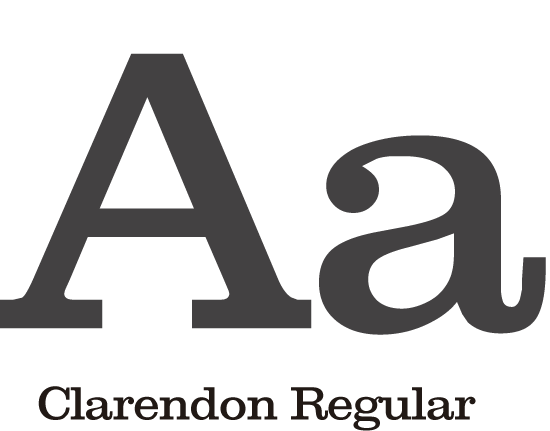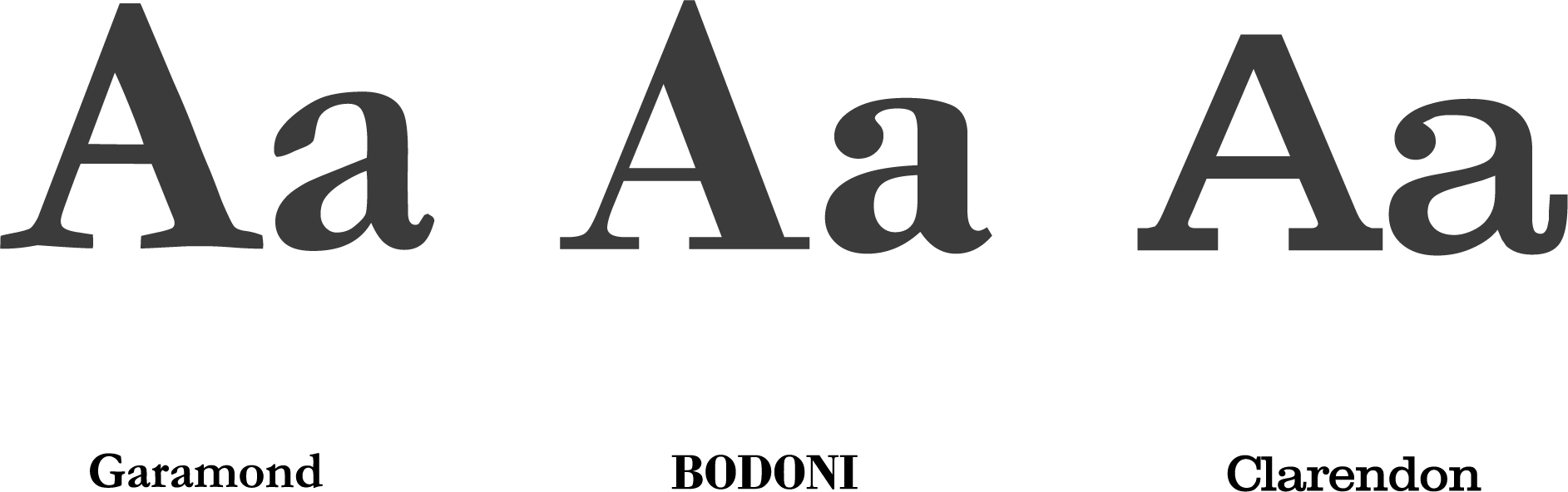
2.- Tipografía Colaborativa – Clasificación Tipográfica, Serif
Segundo Test sobre el correcto uso de la Tipografía en el diseño sobre la segunda animación de los vídeos Tipografía Colaborativa - Clasificación Tipográfica, Serif
1.- ¿Cuáles de las siguientes tipografías presentan Serif?
2.- De acuerdo con la Clasificación Tipográfica ¿Cuáles de las siguientes tipografías pertenecen al estilo Romano Antiguo?
3.- El estilo Egipcio pertenece al grupo tipográfico que presenta Serif, es ideal para títulos y presenta terminaciones cuadradas.
• True
• False
4.- El estilo Romano Antiguo se destacan por su buena legibilidad para textos de largo alcance, originan de inscripciones romanas [blank_start]talladas en piedra antiguo[blank_end].
• talladas en egipcio antiguo
• encontradas en pergaminos antiguos
• talladas en piedra antiguo
5.- De acuerdo con la Clasificación Tipográfica, escribe los estilos correspondientes de las siguientes tipografía con Serif.
• Romano Antiguo
• Romano Moderno
• Egipcio
6.- En la clasificación tipográfica se conocen [blank_start]4 grandes grupos[blank_end], Tipografías con [blank_start]Serif, Sin Serif, Cursivas[blank_end] y [blank_start]decorativas[blank_end].
• 3 grandes grupos
• 4 grandes grupos
• 2 grandes grupos
• Serif, Sin Serif, Cursivas
• Caligraficas, Sin Serif, Cursivas
• Cursivas, Serif, Sin Serif
• Caligrafica
• Cursiva
• Decorativas
8.- De acuerdo con la Clasificación Tipográfica ¿Cuáles de las siguientes tipografías pertenecen al estilo Egipcio?
8.- Ordena las siguientes tipografías con su estilo correspondiente.
• Times New Roman
• Clarendon
• Bodoni
9.- El estilo Romano Moderno presentan un [blank_start]Serif lineal[blank_end] y una [blank_start]gran diferencia[blank_end] entre sus trazos finos y gruesos.
• Serif lineal
• Serif Triangular
• diferencia
• gran diferencia
10.- De acuerdo con la Clasificación Tipográfica ¿Cuáles de las siguientes tipografías pertenecen al estilo Romano Moderno?